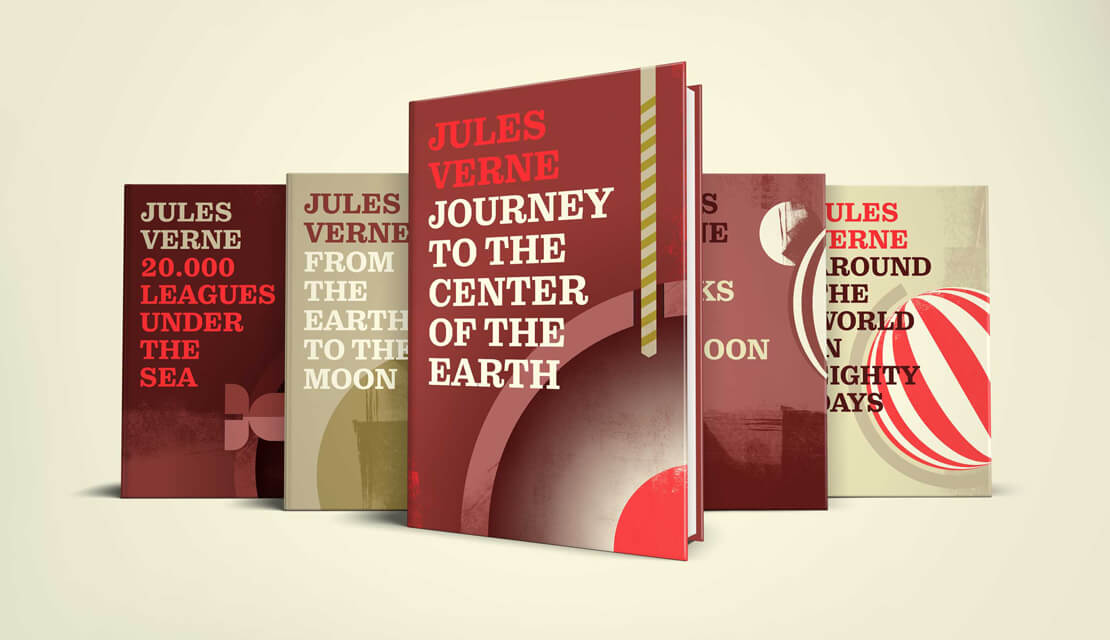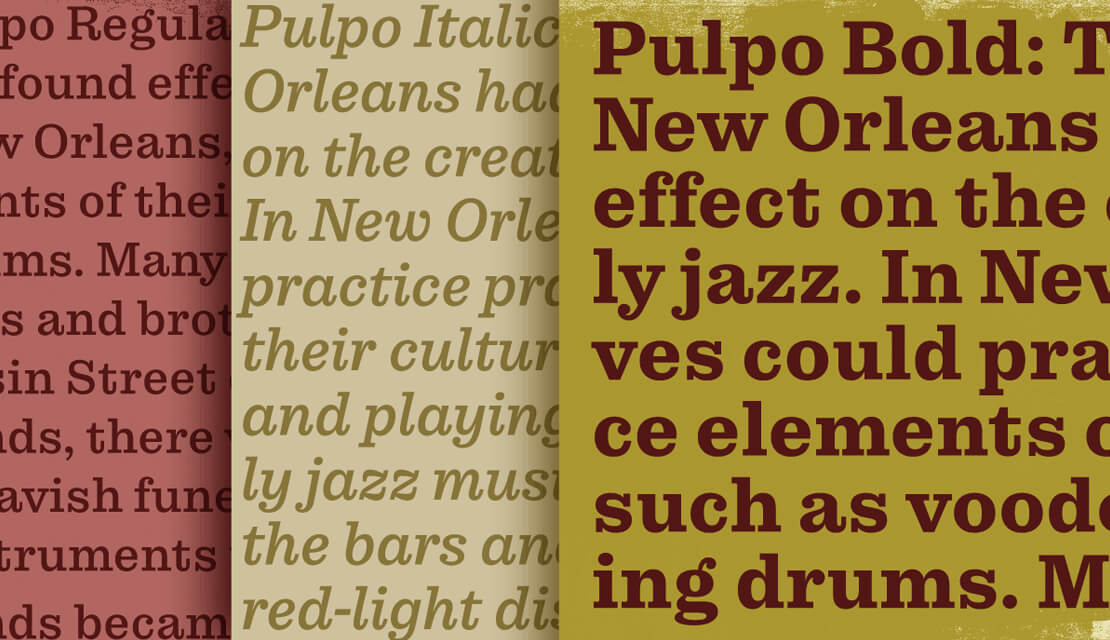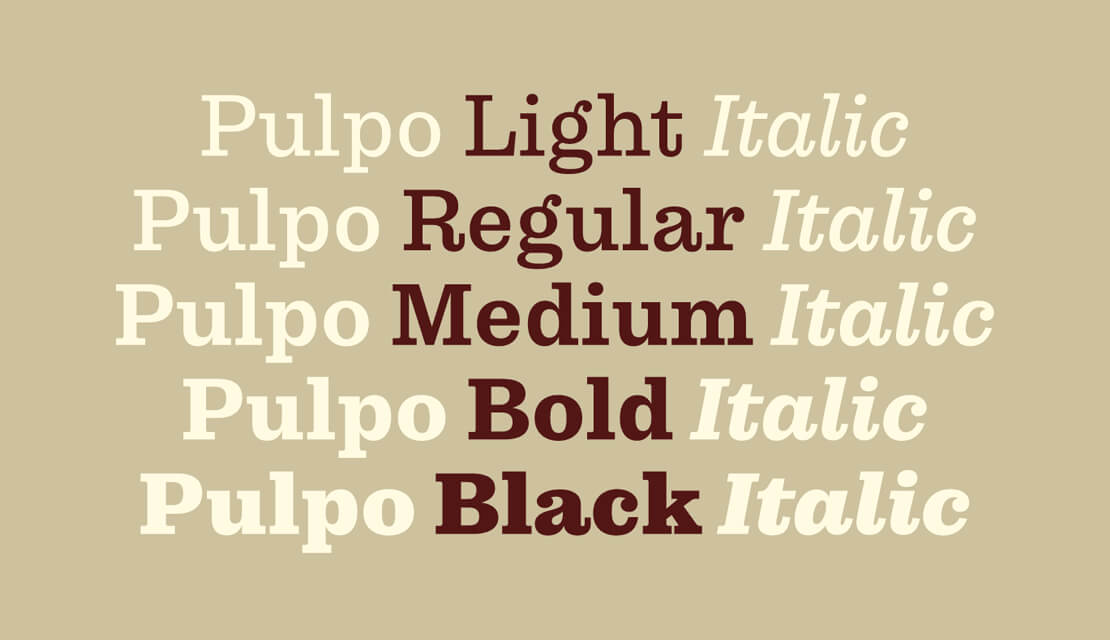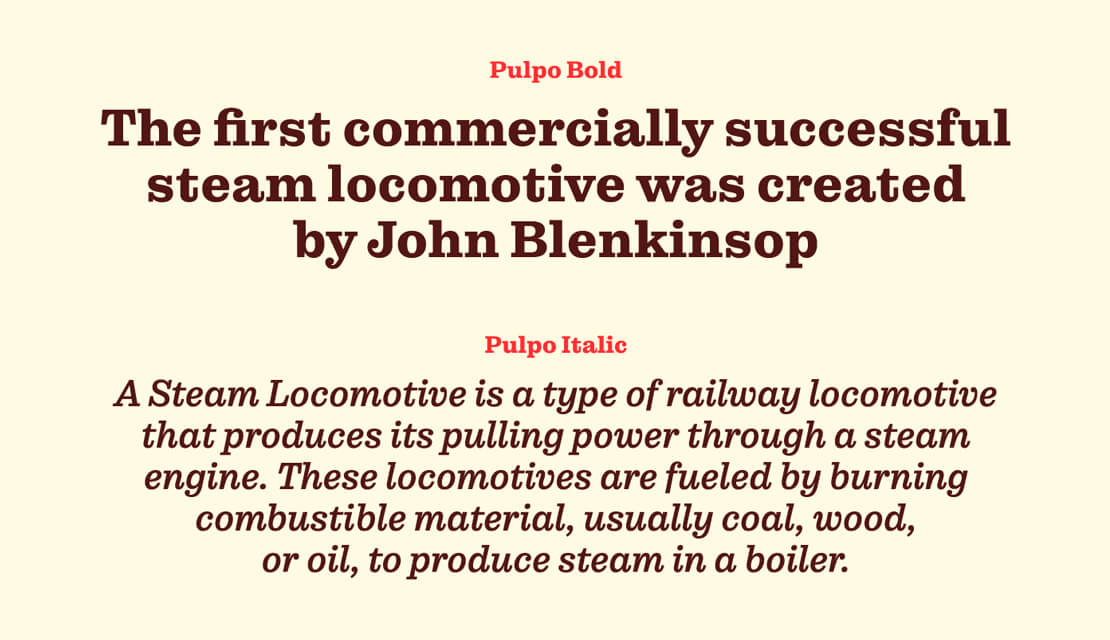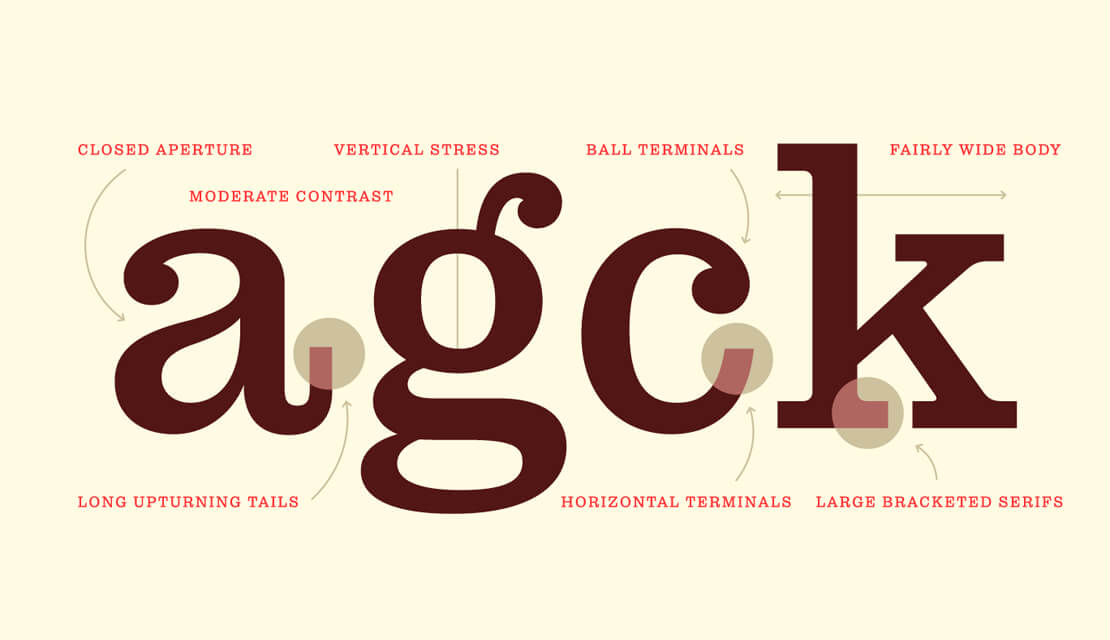
Pulpo – inspiriert von amerikanischer Schriftkultur
Felix Braden stellt seine neue Schriftart »Pulpo« vor. Die Serifenbetonte steht ganz im Zeichen von amerikanischen Schriftdesign.
Pulpo
Amerikanische Art der Schriftgestaltung
Die Schriftart stellt eine Hommage an amerikanische Schriftenklassiker dar. »Pulpo ist eine gut lesbare Clarendon mit dem Skelett der Century Schoolbook.«, sagt der Kölner Type-Designer über seine neue Schriftfamilie. Die Buchstaben sollen vertraute Erinnerungen wecken und zudem ein wenig nostalgisch wirken – wie aus der »guten alten Zeit« eben.
Im Gegensatz zu den amerikanischen Vorbildern, eignet sich die Pulpo durch die moderne Ausrichtung und Gestaltung auch für ausgiebige Lesetexte. Längere Ober- und Unterlängen geben Texten Luft zum Atmen und sorgen für eine bessere Lesbarkeit in kleineren Fließtextgrößen.
Pulpo Schrift Beispiele
Der handgemachte Charakter zieht sich durch alle 10 Schnitte – von Light bis Black, einschließlich der kursiven Varianten. Jeder Font enthält 489 Glyphen, Versal- und Mediäval-Ziffern für Fließtext und Tabellensatz sowie mathematische Zeichen sowie gängige Währungszeichen. »Pulpo« bietet zudem eine umfangreiche Sprachunterstützung für west-, ost- und mitteleuropäischen Sprachen.
Pulpo Font Samples
Entstehungsprozess der Schrift „Pulpo“
2017 entschied sich der Type-Designer Felix Braden, einen ganzen Satz Glyphen für einen manuellen Druckvorgang zu schneiden, der später als digitalisierte Schrift namens »Kontiki« auf MyFonts und als »Pulpo Rust« bei Adobe veröffentlicht wurde.
Als Basis suchte er eine starke Schrift nach dem historischen Clarendon-Muster, die er schließlich selbst auf der Grundlage einer seiner Lieblingsschriftarten (Century Schoolbook) zeichnete. Die Skizzen dieser Clarendon gefielen ihm dann so gut, dass er sich dazu entschied, die Zahl der Schnitte auszubauen, kursive Schnitte zu gestalten und als eigenständige Familie mit dem Namen »Pulpo« herauszubringen.
Entstehung der Schrift Pulpo
Um die aufrechten Schnitte von »Pulpo« zu gestalten, zeichnete Felix Braden über das Skelett der Century Schoolbook und entwarf eine Clarendon, indem er den Kontrast reduzierte und typische Elemente wie lange Aufschwünge und waagerechte Abschlüsse hinzufügte.
Einige Buchstaben mussten komplett überarbeitet werden, da sich die Buchstabenform von der Clarendon-Tradition unterscheidet. Da die Schrift auch in längeren Texten gut lesbar sein sollte, wurden einige dekorative Elemente entfernt, die bei kleinen Textgrößen nicht gut funktionieren. Vor allem die weniger exzentrischen Zahlen unterscheiden sich von den historischen Clarendon-Beispielen.